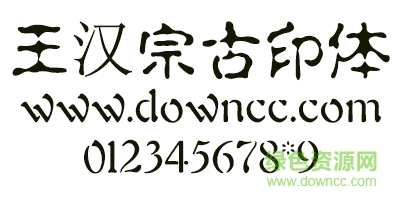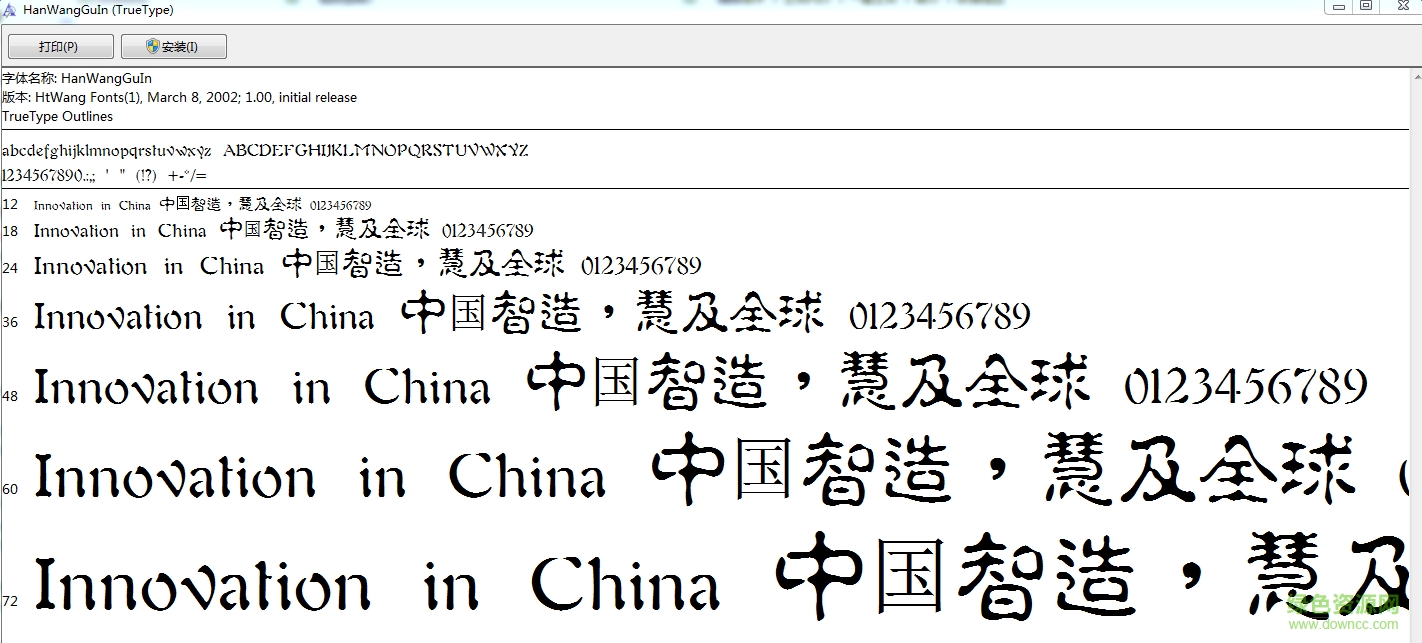
王漢宗古印體字體外形美觀,很受網(wǎng)友們的喜愛!這款字體看起來像印刻在上面的一樣,字體整體比較舒適。多用來進行設(shè)計廣告使用!有需要的用戶歡迎下載安裝。
王漢宗古印體是一款王漢宗類古印字體,字體效果比較正規(guī),印字體給人非常正式的感覺,喜歡行書體字的朋友可以下載使用看看效果如何。